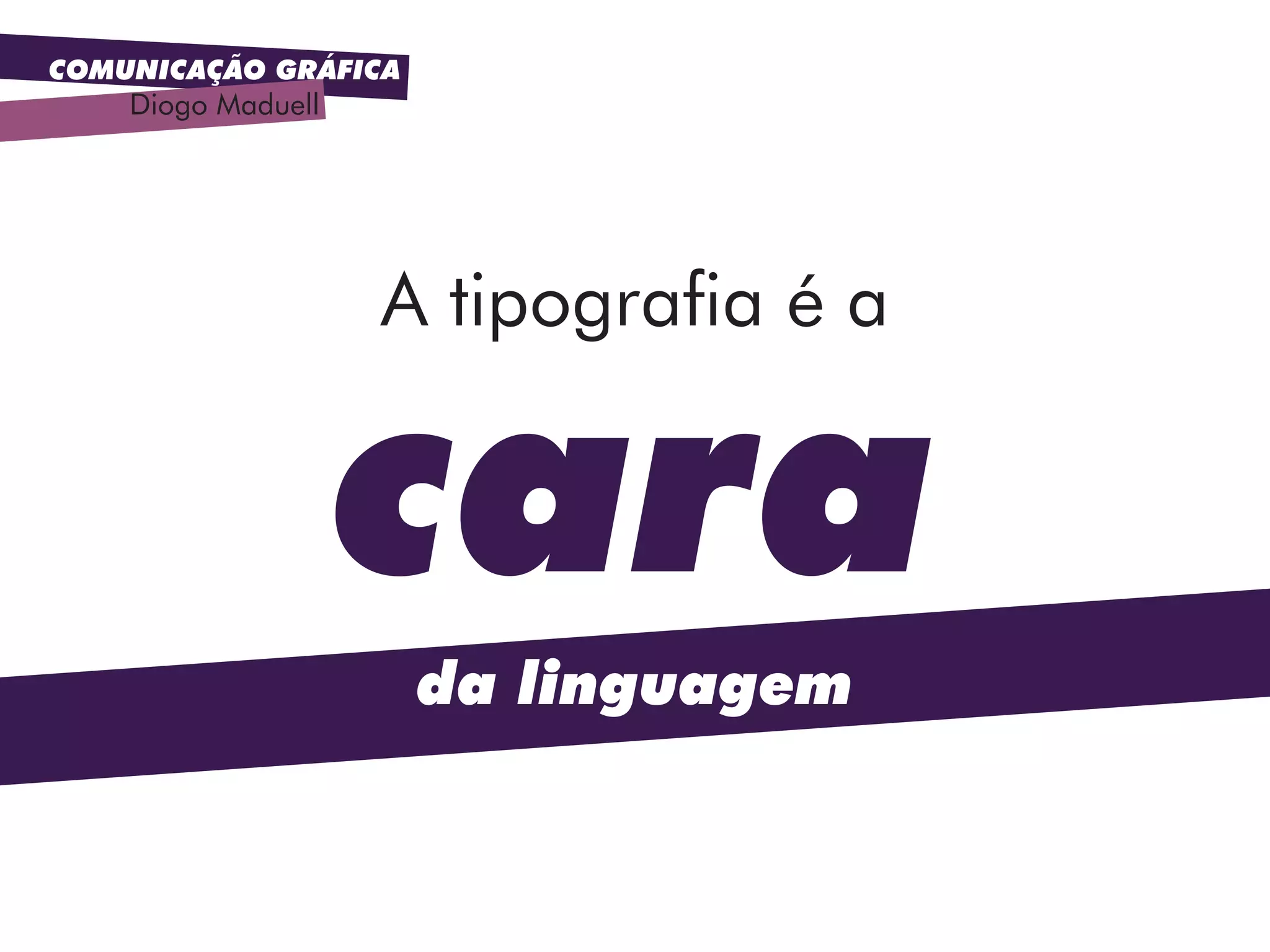
cara
da linguagem
A tipografia é a
SoiS
idiotaS.
y vueStro
profeSor,
imbécil
Sois idiotas.
Y vuestro
profesor, imbécil
Tipos são fala tornada visível.
Abra os olhos e escute.
Tipologia
.Origens
GUTEMBERG
(1450, na alemanha)
.Inventor do tipo móvel
e do processo de impressão
que revolucionou a
reprodução de textos.
Caixas ALTA e baixa
CAIXA ALTA
caixa baixa
Corresponde ao conjunto de caracteres em
letras maiúsculas.
Corresponde ao conjunto de caracteres em
letras minúsculas.
O que alterar?
Corpo
Corpo 100pts
topo da versal
limite inferior
linha das descendentes
altura-x
linha de base
Altura-x - Eixo que define a altura das minúsculas,
correspondente a altura da letra x minúscula.
Altura da Versal - Eixo que define a altura das maiúsculas
Linha de base (Baseline) - Eixo sobre o qual repousam todas as letras
altura
do corpo
100
pontos
O que alterar?
VERSAL
versalete
Outra designação para as maiúsculas.
Caractere maiúsculo com a mesma altura
das minúsculas (altura x).
Versal
versalete
altura-x
Versal e versalete
topo da versal
linha de base
Tipologia – Como Usar
.Caixa Baixa e Caixa Alta
.Textura
.Personalidade
Fonte
Conjunto de caracteres da
ITC Garamond Book
Conjunto de caracteres da
ITC Garamond Italic
Família
Família tipográfica Helvetica
(Max Miedinger, 1957) e suas variações.
Peso
Univers Light 30 pts
Univers Regular 30 pts
Univers Bold 30 pts
Univers Black 30 pts
Univers Light 30 pts
Univers Regular 30 pts
Univers Bold 30 pts
Univers Black 30 pts
Variações de peso da família
Univers (Adrian Frutiger, 1954)
Largura
Univers Condensed 30 pts
Univers Regular 30 pts
Univers Extended 30 pts
Univers
Variações de largura da família
Univers (Adrian Frutiger, 1954)
Univers Compressed 30pts
Univers
Inclinação
Helvetica Regular 40pts
Adobe Garamond Pro Regular 40pts
Helvetica Oblique 40pts
Adobe Garamond Pro Italic 40pts
Variações de inclinação da família Helvetica
(Max Miedinger, 1957)
Variações de inclinação da família Adobe Garamond Pro
Baseada nos tipos de Claude Garamond, cerca de 1550
Tipologia – Classificações
.Com serifa
.Sem serifa
DUPLA
de fontes
Dica: